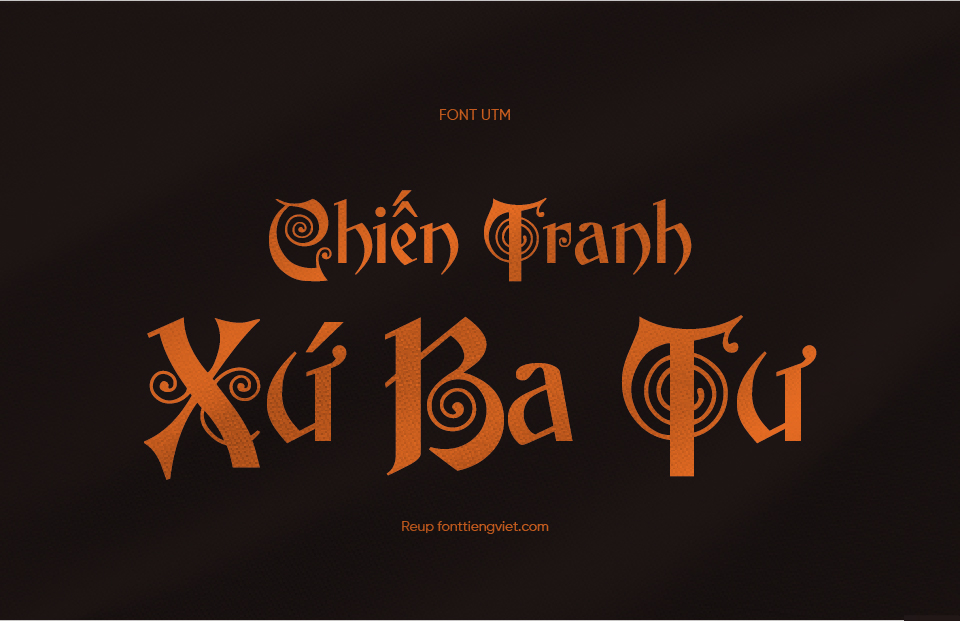
Font việt hóa UTM Dai Co Viet
Giới thiệu về Font việt hóa UTM Dai Co Viet
Trong thế giới đồ họa hiện đại, việc tìm kiếm một bộ Font Miễn Phí mang đậm bản sắc dân tộc là điều vô cùng quan trọng. Font việt hóa UTM Dai Co Viet là một trong những kiểu chữ thư pháp nổi tiếng nhất, được thiết kế dựa trên cảm hứng từ lịch sử hào hùng của dân tộc Việt Nam. Với các đường nét uốn lượn uyển chuyển nhưng không kém phần mạnh mẽ, bộ font này tái hiện lại vẻ đẹp cổ điển của những bản văn khắc đá và bản thảo cổ xưa. Đối với cộng đồng thiết kế tại Việt Nam, đây là lựa chọn hàng đầu cho các dự án văn hóa, giáo dục và nghệ thuật truyền thống.
Đặc điểm nổi bật của kiểu chữ
Bộ chữ này nổi bật với phong cách giả cổ, tạo cảm giác trang trọng và uy nghiêm. Các ký tự được tinh chỉnh kỹ lưỡng để phù hợp với bảng mã Unicode, giúp người dùng gõ tiếng Việt một cách mượt mà không bị lỗi font. Đây là điểm cộng lớn cho các giáo viên và học sinh khi thực hiện các bài thuyết trình về lịch sử hoặc báo tường nhân dịp lễ hội.
Ứng dụng của Font việt hóa UTM Dai Co Viet trong thực tế
Nhờ vẻ ngoài độc đáo, Font việt hóa UTM Dai Co Viet thường được sử dụng trong việc thiết kế bìa sách, bằng khen, hoặc các tiêu đề phim cổ trang. Trong môi trường học đường, các bạn học sinh có thể dùng font chữ này để làm nổi bật tên đề tài hoặc trang trí thiệp mời sự kiện. Sự kết hợp giữa nét chữ thư pháp và kỹ thuật đồ họa hiện đại mang lại hiệu ứng thị giác cực kỳ ấn tượng, giúp truyền tải thông điệp một cách sâu sắc và giàu cảm xúc hơn.
Lưu ý khi sử dụng font chữ thư pháp
Mặc dù rất đẹp, nhưng bạn nên sử dụng font này cho các tiêu đề lớn hoặc đoạn văn ngắn để đảm bảo tính dễ đọc. Tránh dùng cho các văn bản dài vì độ phức tạp của nét chữ có thể gây mỏi mắt cho người xem.